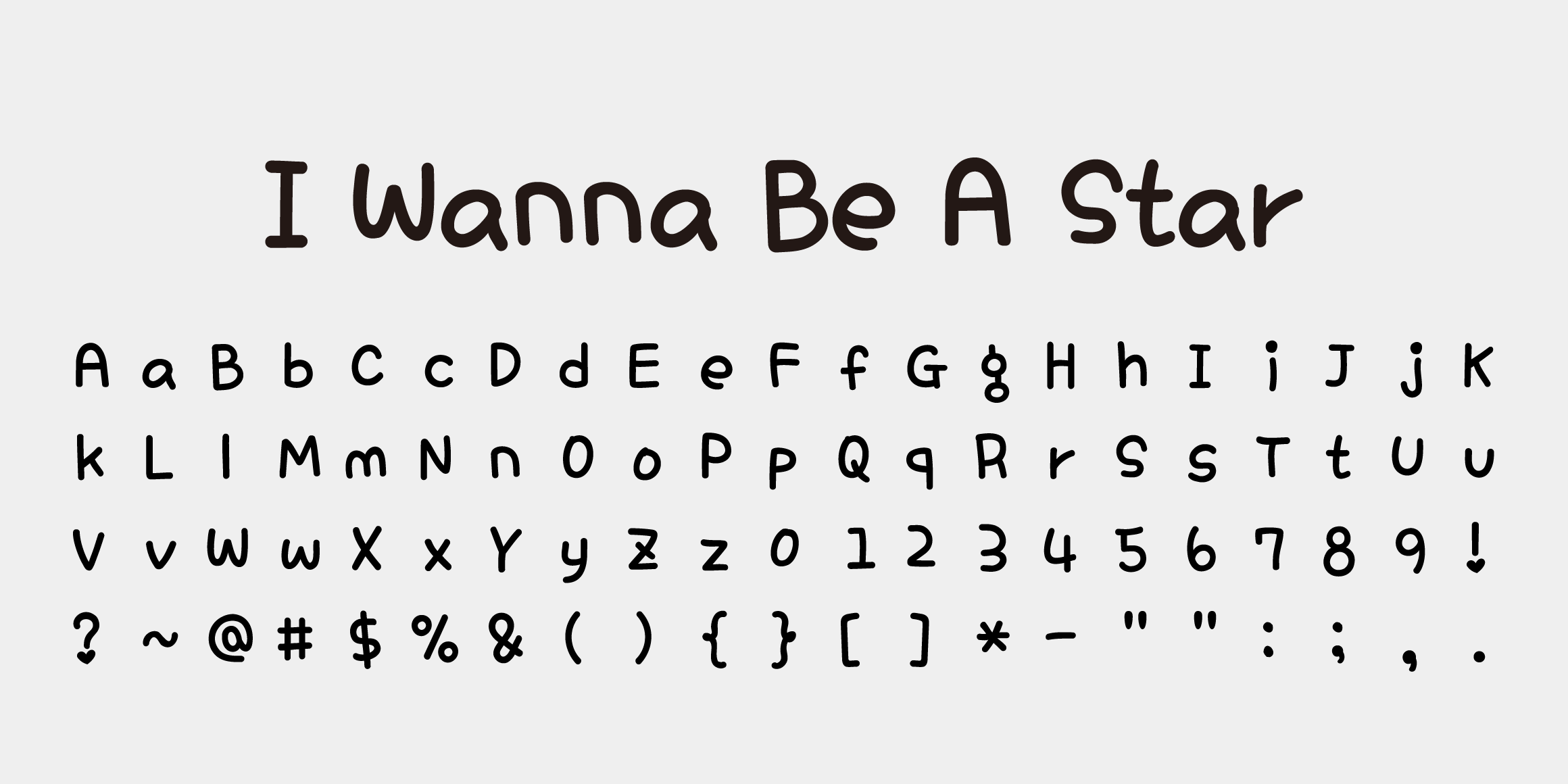
Yoon 화이트사탕
Yoondesign
마치 하트 모양 막대사탕을 글자마다 쏙쏙 꽂아놓은 것 같죠? 종종 보이는 미소 장식은 또 어떻고요! 첫 데이트, 첫 출근, 첫 등교. 어쩐지 설레는 첫 순간에 어울리는 사랑스러운 폰트. 화이트사탕체로 일상의 설렘을 기록해보세요.
• 2007
• 윤디자인
• 한글 11,172자 / 라틴 95자 / 부호 985자
• Yoon 화이트사탕 / Yoon Hwaiteusatang